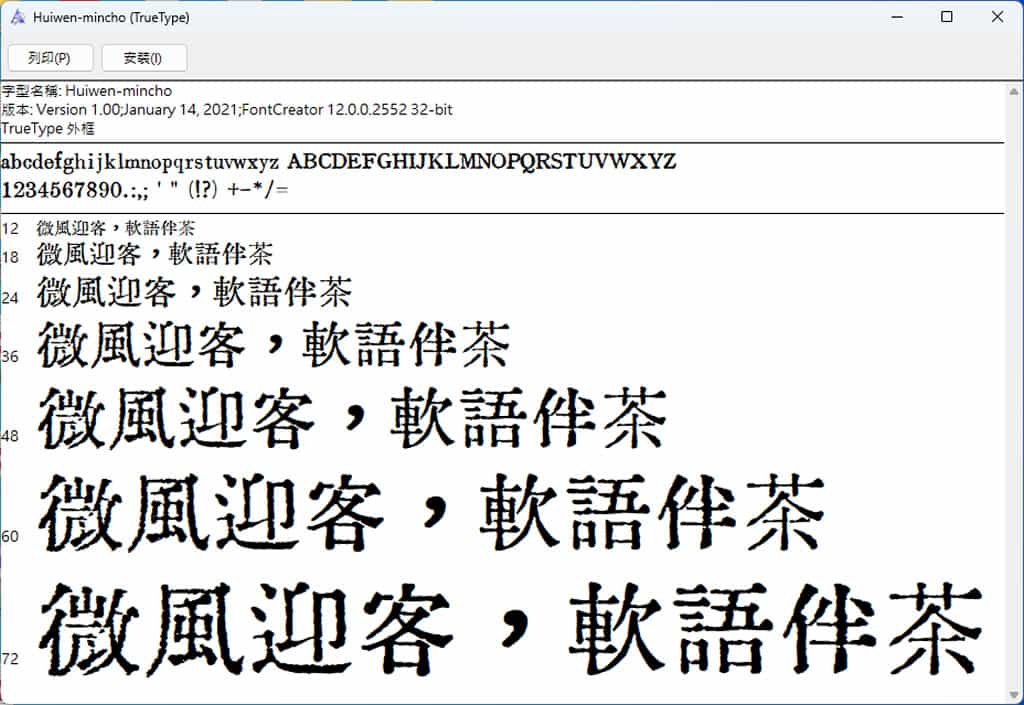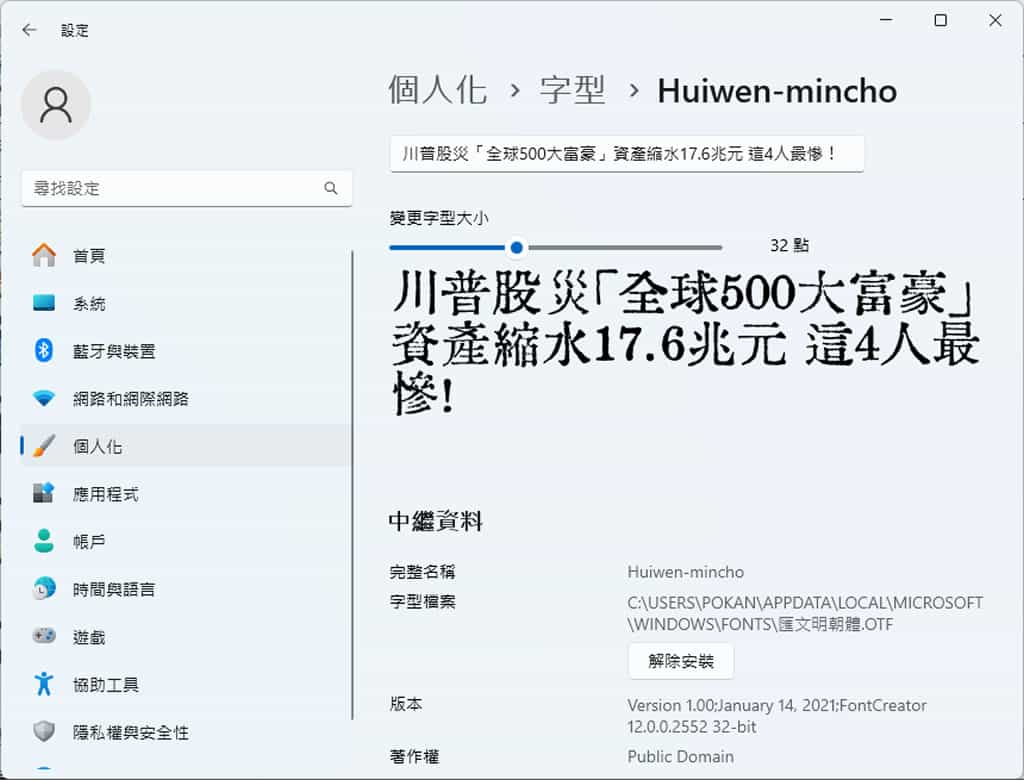
匯文明朝體( Huiwen-mincho )是一款再現舊鉛字印刷風格的免費繁體字體,適用於印刷設計、電子書、網站排版與 UI 介面。該字體支援中國 GB2312 標準、台灣《常用國字標準字體表》,並涵蓋日本常用漢字、人名用漢字及表外漢字的新字體,適合多語系環境使用。根據官方說明,匯文明朝體的設計源自 Oradano 明朝,其拉丁字母、符號、平假名、片假名及部分漢字均來自該字體。然而,開發者以 Oradano 明朝為基礎框架,逐步替換其中的字形,最終打造出全新的匯文明朝體。
匯文明朝體是一個能夠輕鬆再現舊鉛字印刷風格的免費中文字體,同時支援簡體與繁體中文,適用於印刷設計、螢幕顯示、電子文檔嵌入及設備應用。此外,該字體可自由轉發與使用,無論是個人專案還是商業應用,都能帶來懷舊且專業的視覺效果,是熱愛傳統印刷風格與多語系設計者的理想選擇。